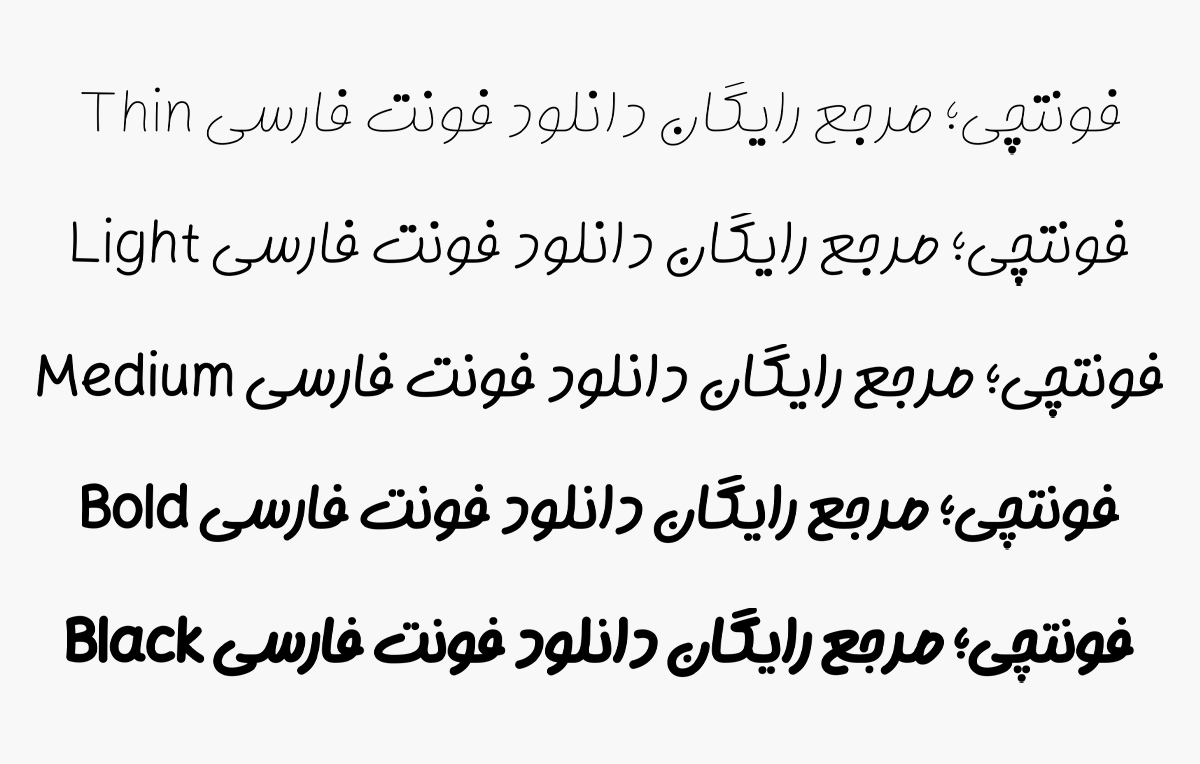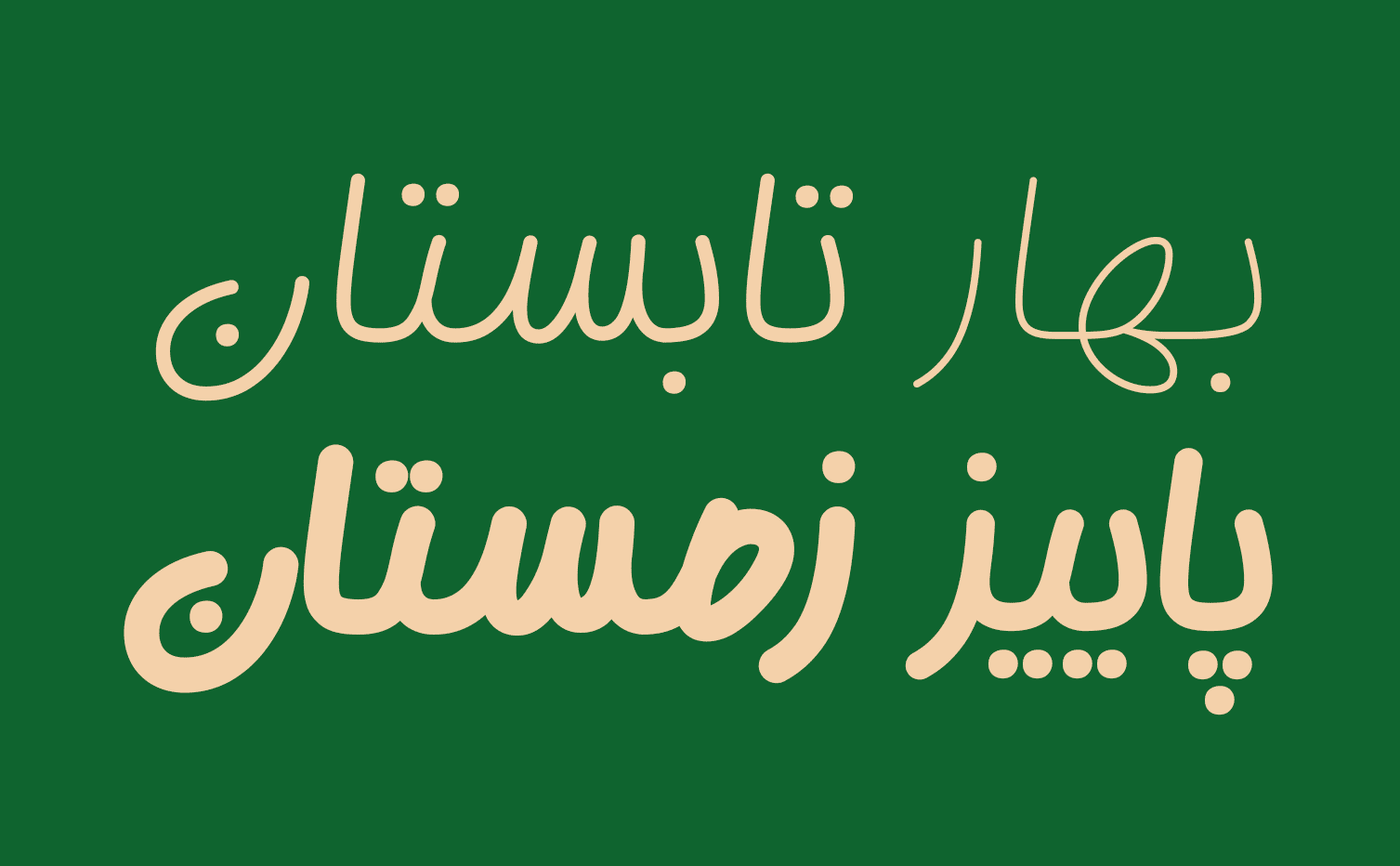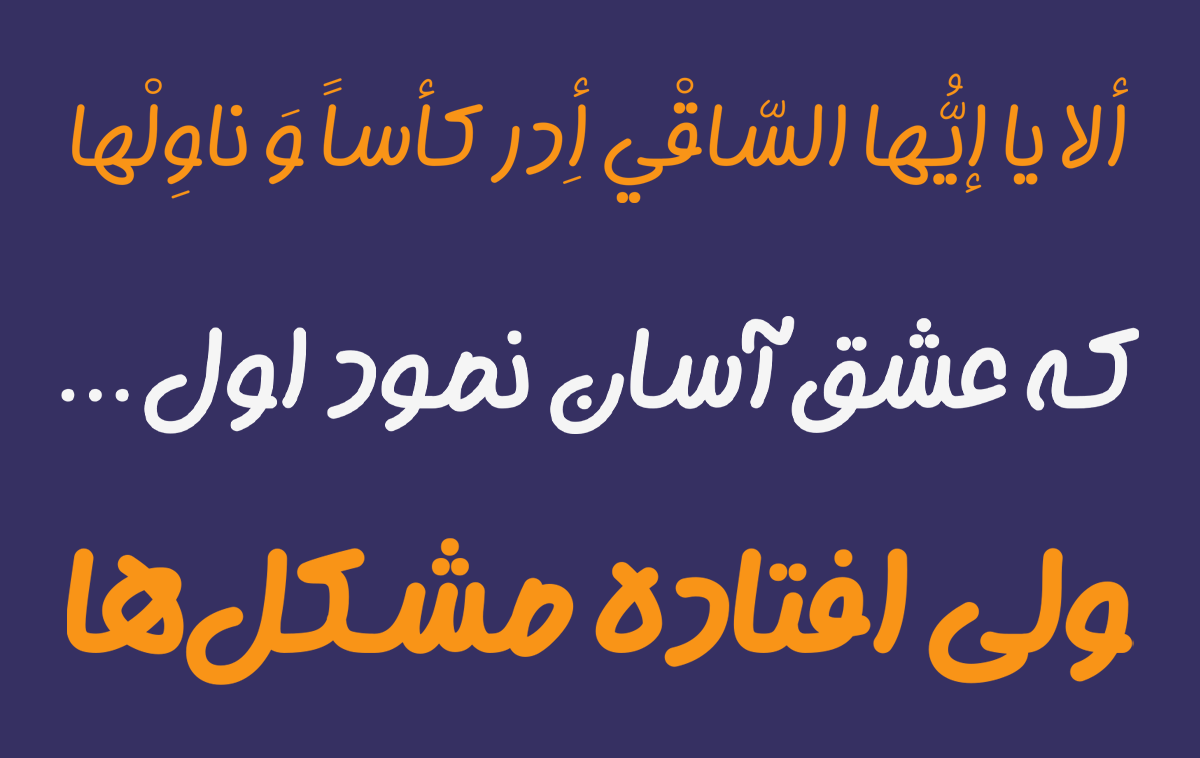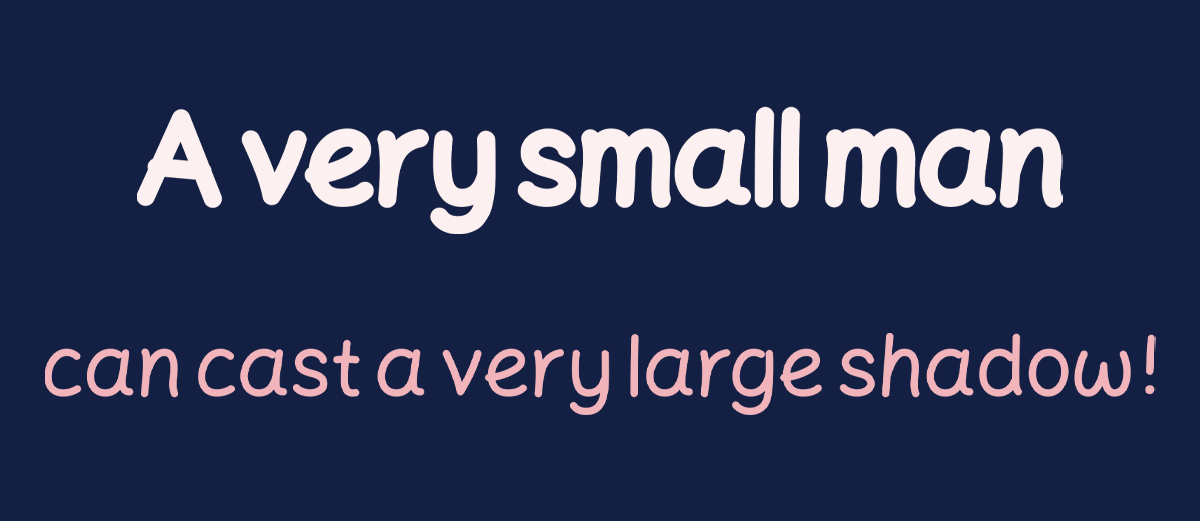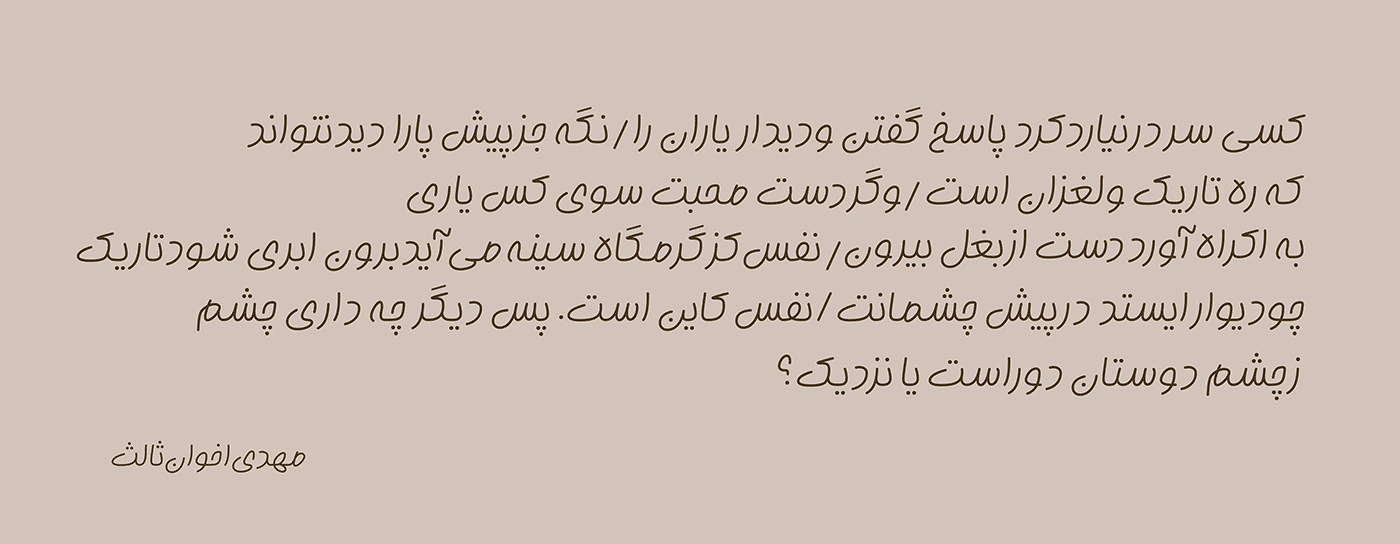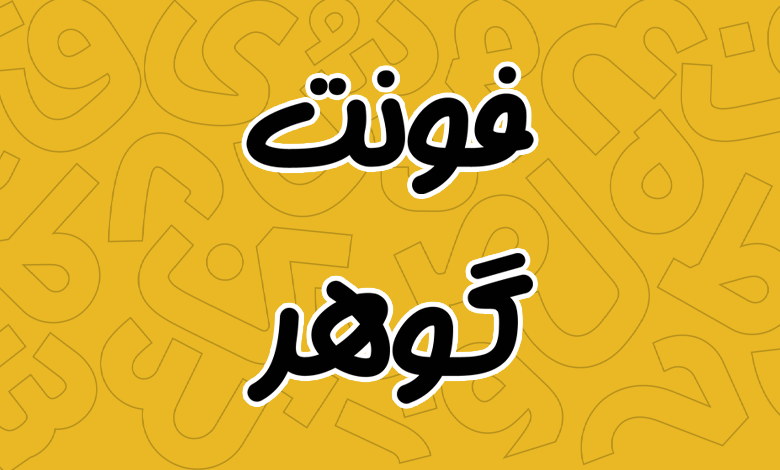
فونت گوهر (Gohar)
فونت گوهر (به انگلیسی: Gohar) قلمی دست نویس در گروه فونتهای مناسب متن و تبلیغات است که علاوه بر زبان فارسی، از زبان عربی، انگلیسی، کردی و اردو هم که رسط خط فارسی دارند پشتیبانی میکند. این فونت دست نویس دارای ساختاری نرم و دوستانه است که بهدور از هر گونه اغراق و بزرگنمایی برای تبدیل شدن به یک فونت فانتزی است.
قلم گوهر توسط مصطفی اوجی که جزو قدیمیترین طراحان تایپفیس فارسی هستند طراحی شده است و توسعه آن را به منظور استفاده در نرمافزار امین عابدی به سرانجام رسانیده است. این قلم ساختاری با ضخامت ثابت (مونولاین) دارد که برای استفاده در متون بلند عالی است.
در ادامه این نوشته از سایت فونتچی به نقد و بررسی کامل فونت گوهر خواهیم پرداخت؛ فونتی که میتوانید از آن به عنوان یک قلم دستنویس برای تبلیغات، طراحی انواع پوستر و بنر، چاپ جلد کتاب و هر مضمون دیگری که نیاز به یک قلم دست نویس ساده و در عینحال با خوانایی زیاد داشته باشید استفاده کنید.
بررسی و دانلود فونت گوهر (Gohar)
فونت گوهر ساختار فشرده و اصطلاحا جمع و جور دارد که بهدور از بزرگنمایی و فاقد کنتراست وزنی ساخته شده است. برای همین سطرهای منسجم و فشردهای هم دارد. حرکات حروف به رغم رهایی حرکات قلم، فرمهای کنترل شدهای دارند.
سبک طراحی و وزن فونت گوهر
فونت گوهر در ۵ وزن نحیف، لایت، متوسط، بولد و سیاه طراحی شده است که با کمک آن میتوانید کنترل خوبی روی دسته بندی نوشتهها داشته باشید.
در شکل ساختاری این قلم دندانهها و گردی حروف دارای زاویه نرم و خاصی هستند؛ طوری که نه بیش از حد زوایای تند و کنترل نشدهای به خود گرفته و نه اینکه آزادی قلم از آن سلب شده است. نقاط در این قلم چسبان نبوده و به صورت گرد در نظر گرفته شدهاند.
در خطوط قائم حروف شاهد یک زاویه نسبتا جزئی به سمت راست هستیم و دندانهها نیز ساختاری کشیدهتر دارد که همین باعث میشود فونت به طور کلی کمی ساختار فشرده به خود بگیرد؛ خصوصا اینکه در دندانههای دارای نقطه در حروفی مثل «ث، ش، ت» این فشرده بودن با نزدیک شدن به خط بالایی بیشتر خود را نشان میدهد.
پشتیبانی از زبان عربی و انگلیسی
فونت فارسی گوهر محدود به این زبان نیست. قبل از هر چیزی از سایر زبانهای مبتنی بر رسم خط فارسی همچون عربی، کردی و اردو هم پشتیبانی میکند که این پشتیبانی هم شامل حروف و ساختارهای مشترک بوده و هم اینکه حروف متفاوت در هر زبان را شامل میشود.
برای مثال در زبان عربی که حروفی مثل «ک، ی، ه، ؤ، ئ» یا اعداد «۴۵۶» که متفاوت از زبان فارسی هستند در تمامی گلیفهای این فونت پیادهسازی شدهاند تا متناسب با زبان انتخابی صفحه کلید بر مبنای استاندارد همان زبان تایپ شوند.
اعراب و تفاوتهایی که برای هر زبان از نظر قرار گیری نقاط روی یا زیر برخی حروف یا استفاده از گلیفهای تزئینی در این فونت برای زبانهای کردی و اردو که زیاد رایج است رعایت شده است.
در نسخه انگلیسی فونت گوهر هم شاهد همان ساختار دست نویس هستیم. برای زبانهای لاتین از فونت دیگری استفاده نشده یا اینکه وام گرفته شده از قلم دیگری نیست. تمامی حروف برای این زبان نیز همان سبک طراحی نسبتا فشرده را دارا هستند.
این میزان پشتیبانی از زبانهای مختلف محدود به حروف نبوده و شامل اعراب، کاراکترهای خاص و اعداد برای هر زبان میشود.
مناسب تبلیغات و متن بلند
از این قلم میتوانید استفادههای زیادی داشته باشید. تفاوتی ندارد که در حوزه تبلیغات از این قلم استفاده کنید یا اینکه نیاز به یک فونت دست نویس برای صنعت چاپ و مطبوعات مثل کتاب کودک و نوجوان داشته باشید.
در هر صورت اگر احساس میکنید که استفاده از یک قلم دستنویس میتوان از هر نظر روی محتوای شما از جهات مختلفی مثل فروش، جلب توجه کاربر و ایجاد ارتباط بهتر با وی موثر باشد، استفاده از این قلم را به شما پیشنهاد میکنیم.
این قلم به لطف پشتیبانی از ۵ وزن مختلفی که دارد خوانایی متون را افزایش خواهد داد و برای سایز فونت کوچک تا خیلی بزرگ مناسب است. هر چند که زیبایی آن در وزنهای سنگین و اندازه بزرگ بهخاطر کنتراست بهتر و سیاهتر به نظر رسیدن قلم بیشتر خود را نشان میدهد.
اگر ساختار سایت شما وبلاگی است یا سایتی در حوزه کودک و نوجوان دارید، استفاده کلی از این قلم میتواند به دلیل ایجاد ارتباط بهتر و صمیمیتر با مخاطب روی رابط کاربری و محوریت فعالیت شما موثر باشد.
به لطف پشتیبانی از وزنهای مختلف نیز میتوانید از وزنهای سیاه و بولد در بخشهایی مثل عنوان مطالب، تیترها، نثل قول و هر بخشی که فکر میکنید ضروری است توجه مخاطب را به آن معطوف کنید استفاده کنید. چنین چیزی هم به کاربر کمک میکند بین متون طولانی گم نشود و هم اینکه با افزایش خوانایی به دلیل وجود چند وزن مختلف، به کاربر در یافتن بخشی از محتوا که به آن نیاز دارد کمک خواهد کرد.
جدیدترین نسخه فونت دست نویس گوهر ورژن ۱.۰ است که در آذر ۱۴۰۱ منتشر گردیده است. از این قلم میتوانید به عنوان یک فونت دستنویس دوستانه با ساختاری نرم در محیطهای مختلفی همچون متنهای کوتاه تا بلند، شعارهای تبلیغاتی، بستهبندی محصول و کتاب کودک و نوجوان استفاده کنید.